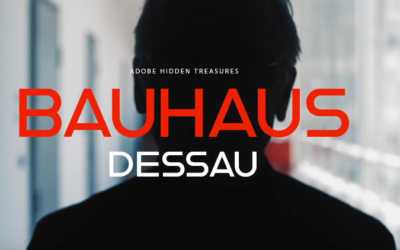
Trésors cachés de la créativité : Adobe redonne vie à des polices d’écriture anciennes
Adobe a lancé officiellement hier la deuxième édition de sa campagne Hidden Treasures of Creativity, intitulée The Lost Alphabets of Bauhaus Dessau....
Adobe a lancé officiellement hier la deuxième édition de sa campagne Hidden Treasures of Creativity, intitulée The Lost Alphabets of Bauhaus Dessau. Pour l’occasion, Adobe s’est associé à l’institut de design Bauhaus Dessau en exploitant des œuvres inachevées de cinq maîtres du design : Alfred Arndt, Carl Marx, Joost Schmidt, Reinhold Rossig et Xanti Schawinsky. […]